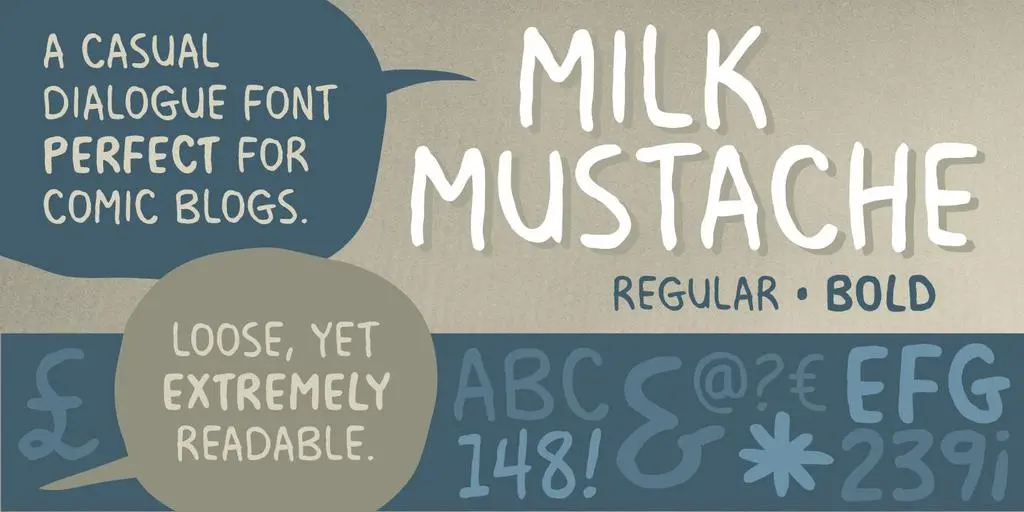
Milk Mustache BB Font Family
A fonte ‘Milk Mustache BB Font Family’ é perfeita para quem quer adicionar um toque alegre e informal às suas criações digitais. Especialmente indicada para blog-style comics, esta fonte casual manuseia diálogos de uma maneira leve mas ainda muito legível. Ela vem com o Regular e Bold, proporcionando flexibilidade para diferentes usos. Não é difícil perceber por que a Hamilton escolheu este nome para a fonte – sua simplicidade e frescor fazem dela um verdadeiro charminho no mundo das fontes de script. Com seu toque amigável e descompromissado, esta fonte se destaca entre as demais. Perfeito tanto para anúncios em suas páginas do blog quanto para criar uma personalidade única nos seus trabalhos digitais. Através deste ‘Milk Mustache BB Font Family’, Hamilton criou uma fonte que não só mantém a leitura confortável, mas também adiciona um toque de frescor e descontração às suas criações.